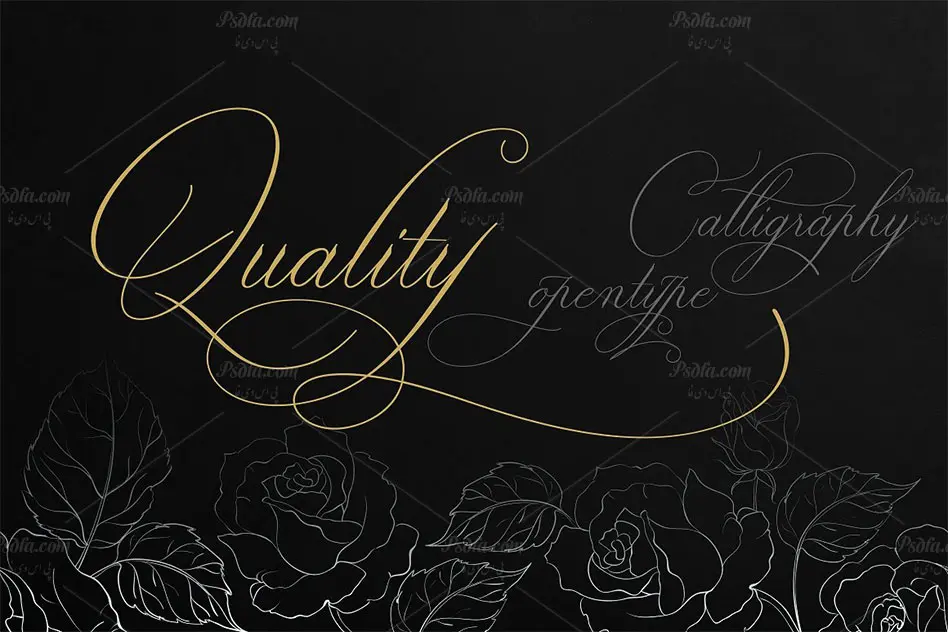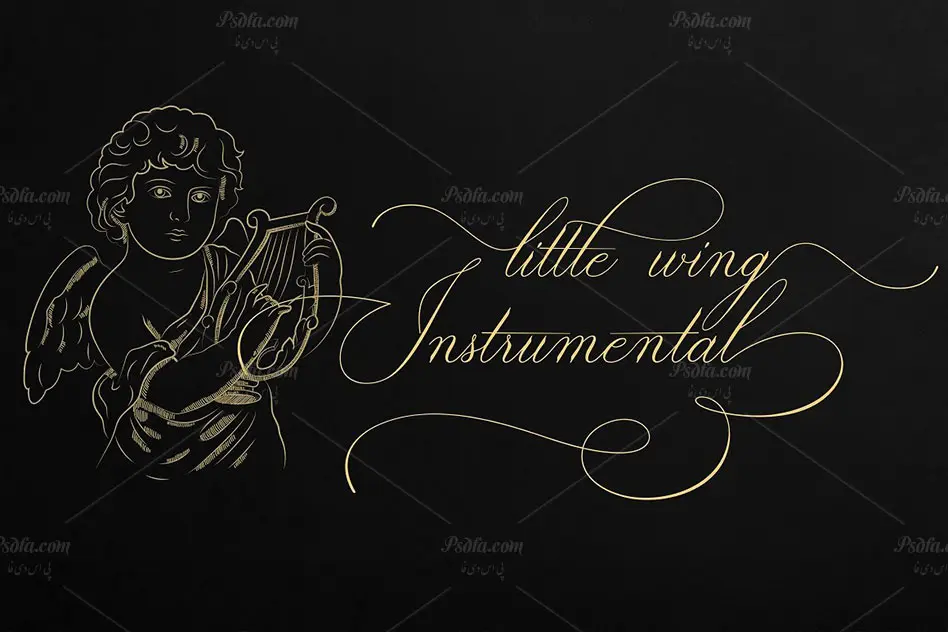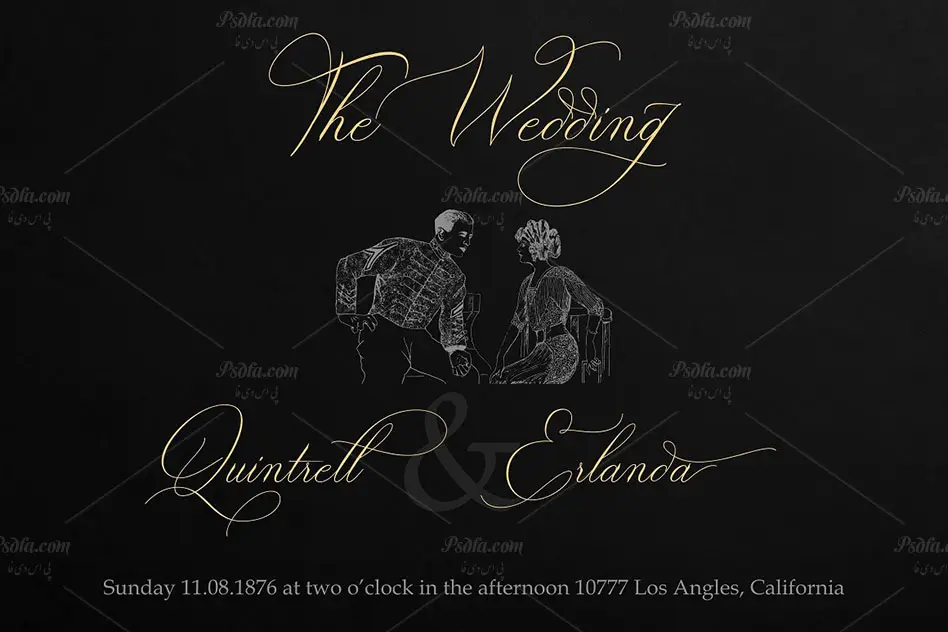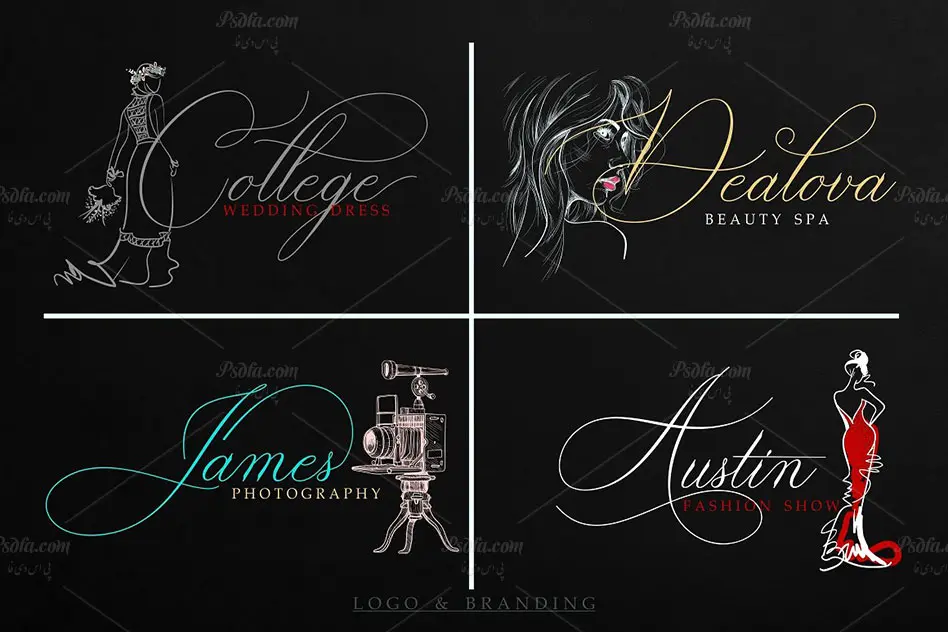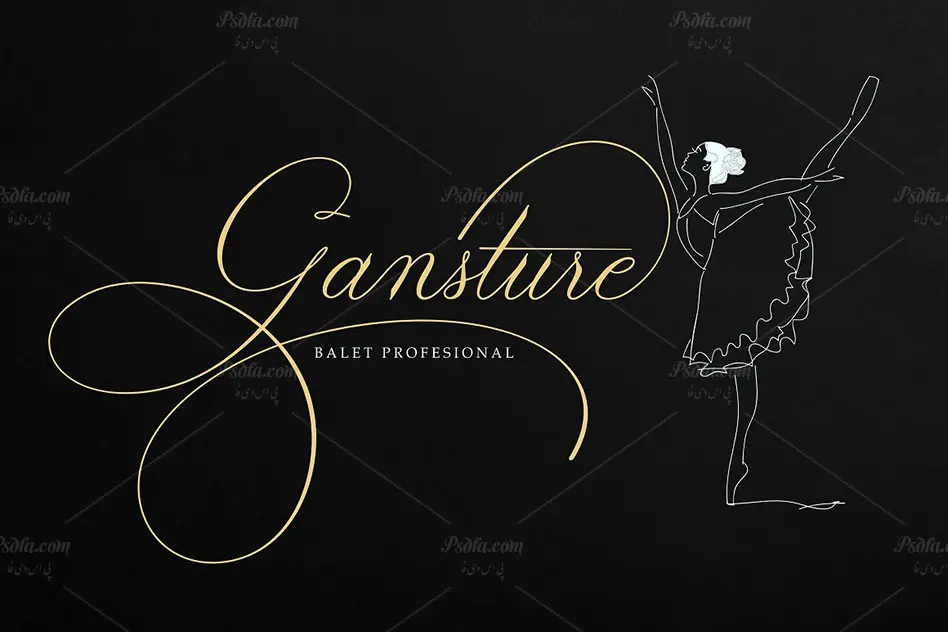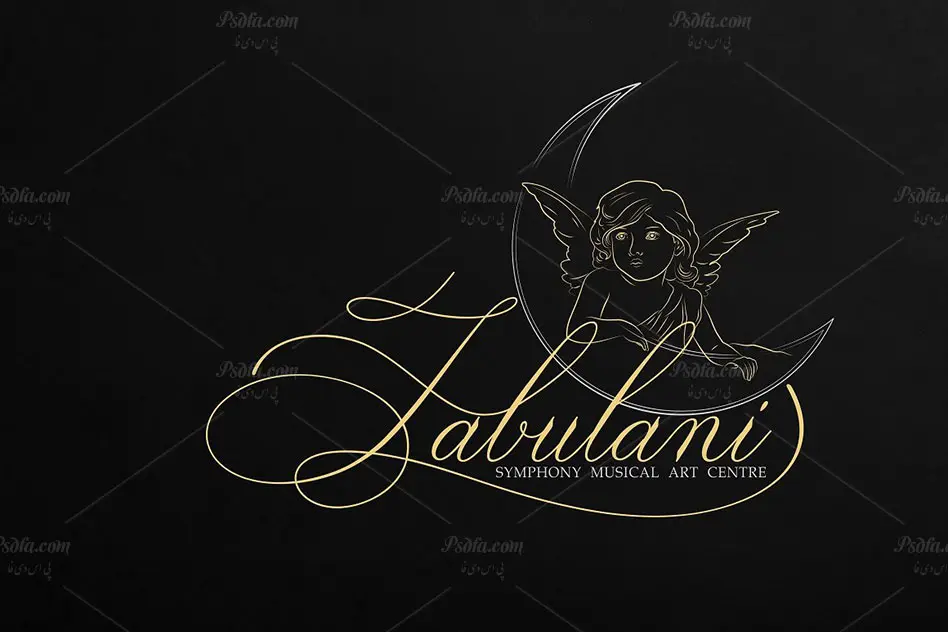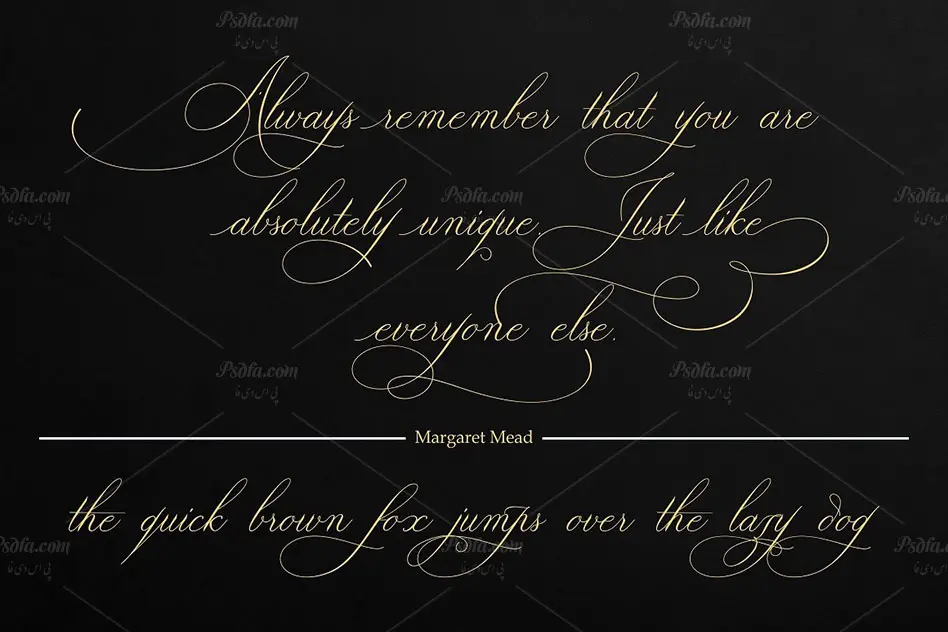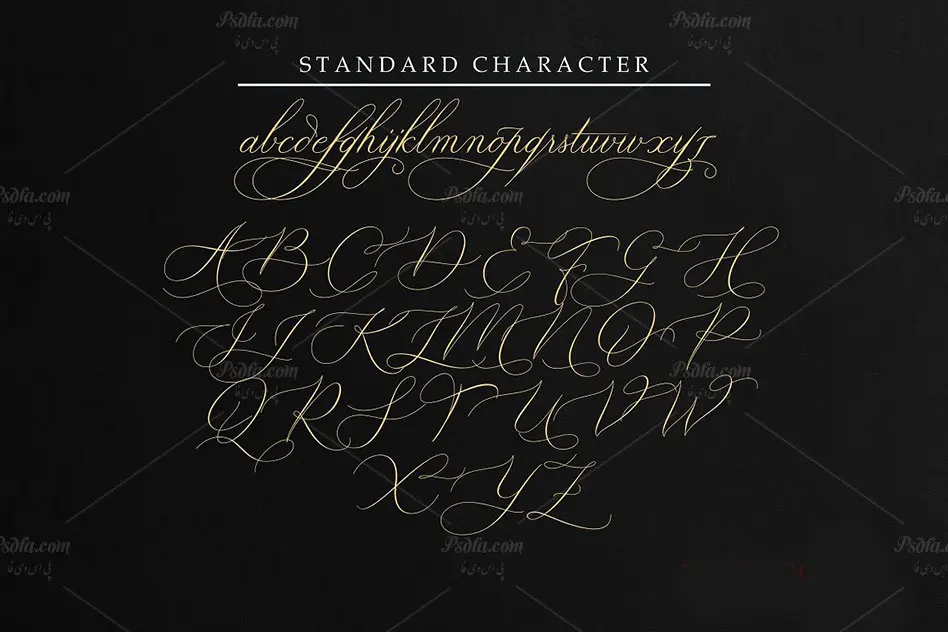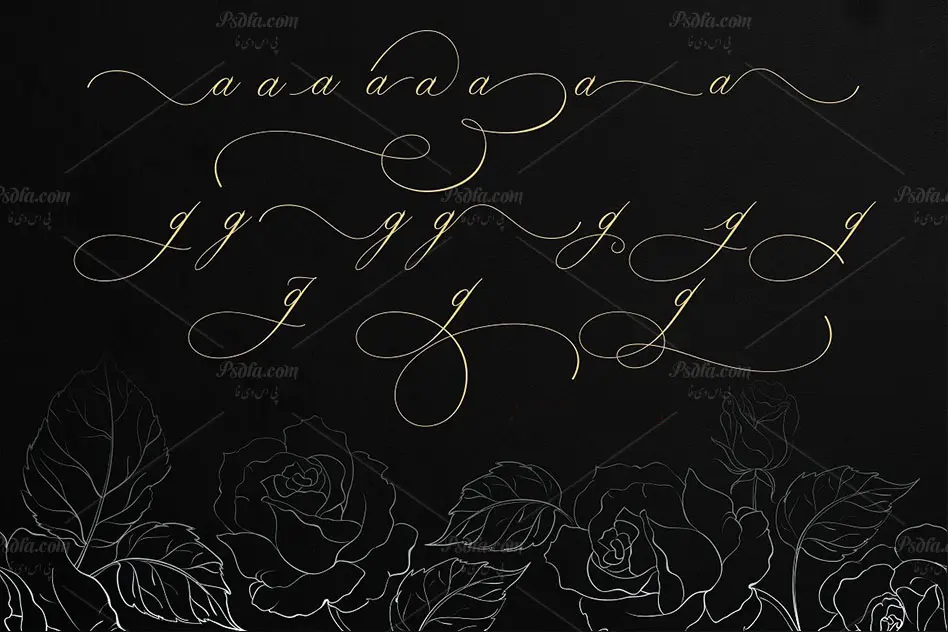
در این مطلب شاهد فونت انگلیسی Bulgattie مناسب برای طراحی انواع کارت عروسی و کارت تبریک می باشید. فونت انگلیسی Bulgattie یکی دیگر از سری فونت های فوق العاده زیبای انگلیسی می باشد که از آن می توان در طراحی و گرافیک به خصوص طراحی انواع کارت عروسی ، کارت پستال ، کارت تبریک ، انواع پوستر و … استفاده نمود. این فونت زیبا با دو فرمت ttf و otf در سایت قرار گرفته است که پس از نصب آن در پوشه فونت های سیستم می توانید به طور مستقیم در تمام نرم افزارهای گرافیکی و ویرایشگر متن از جمله نرم افزار فتوشاپ ، مجموعه نرم افزار آفیس و … از آن استفاده کنید.
- کیفیت بالای فونت
- مناسب جهت طراحی انواع کارت عروسی ، کارت تبریک ، کارت پستال و انواع پوستر